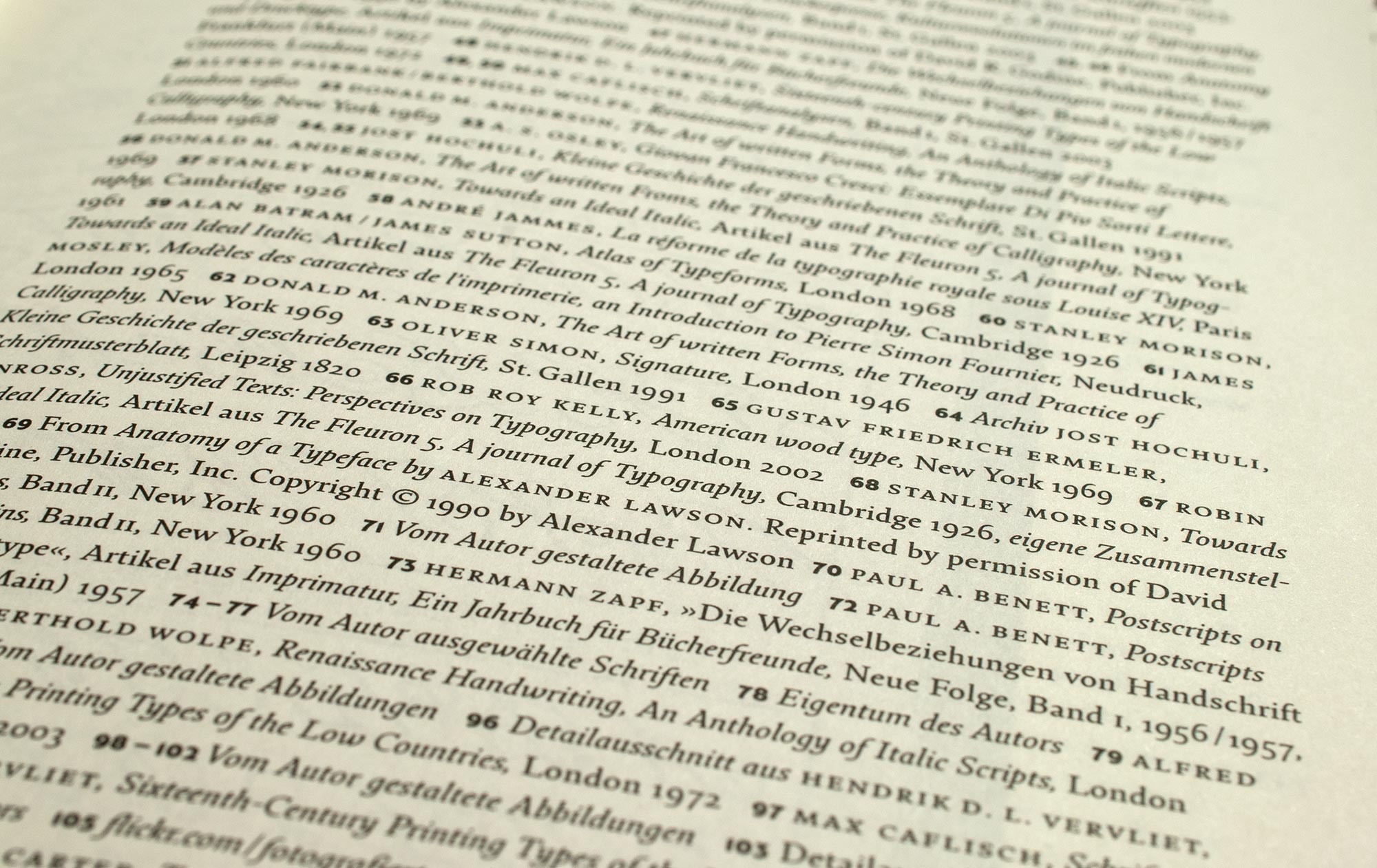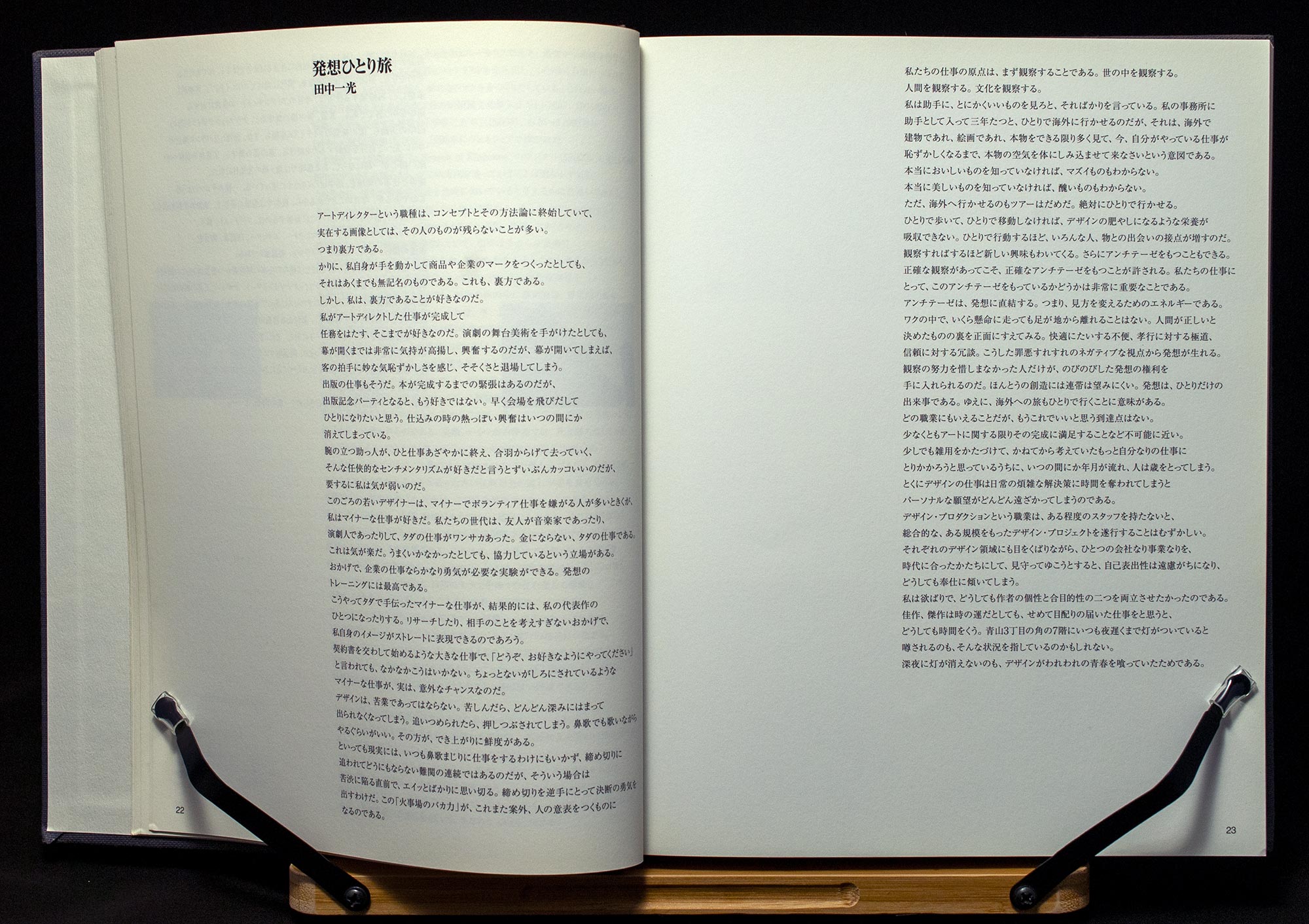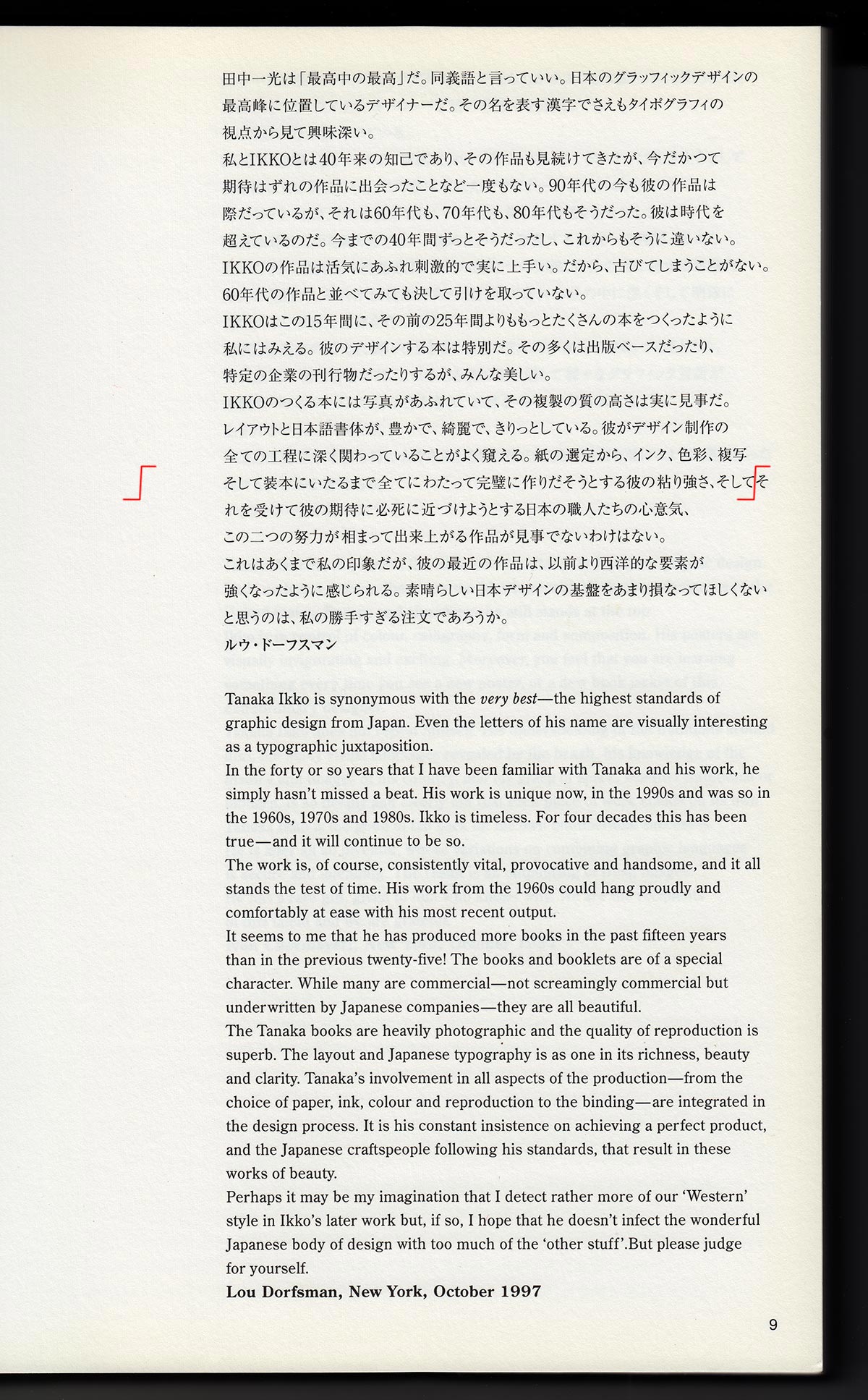
Flattersatz und Kursive im Japanischen
»Kursiv – Was Typographie auszeichnet« von Hendrik Weber, 2010
Was in der europäischen Typografie selbstverständlich ist, muss es deswegen noch lange nicht auch in der japanischen sein. Typische Beispiele.
Japanische Texte flattern nicht
In den meisten geschriebenen Sprachen der Welt werden Wörter voneinander getrennt. Die Zeilen werden bei Wortfugen umgebrochen. Die Zeilenlänge variiert ständig, weil die Wörter unterschiedlich lang sind. So entsteht der Eindruck, dass die Texte flattern. Aber Japanisch wird ohne Leerzeichen geschrieben und abgesehen von wenigen Ausnahmen kann ein Zeilenumbruch mitten im Wort nach jedem Schriftzeichen erfolgen. Deswegen gibt es in der Regel im Japanischen keinen Flattersatz, wie er in westlichen Texten verbreitet ist. Für japanische Texte wird in den allermeisten Fällen Blocksatz verwendet.
Wo jedoch kein Bocksatz erwünscht ist, z.B. bei diversen Überschriften, Teasern oder Bildunterschriften, werden Texte in Form von Flattersatz gesetzt, wobei sich die Zeilenumbrüche nicht nach dem verfügbaren Platz, sondern immer nach inhaltlichen Erwägungen richten.
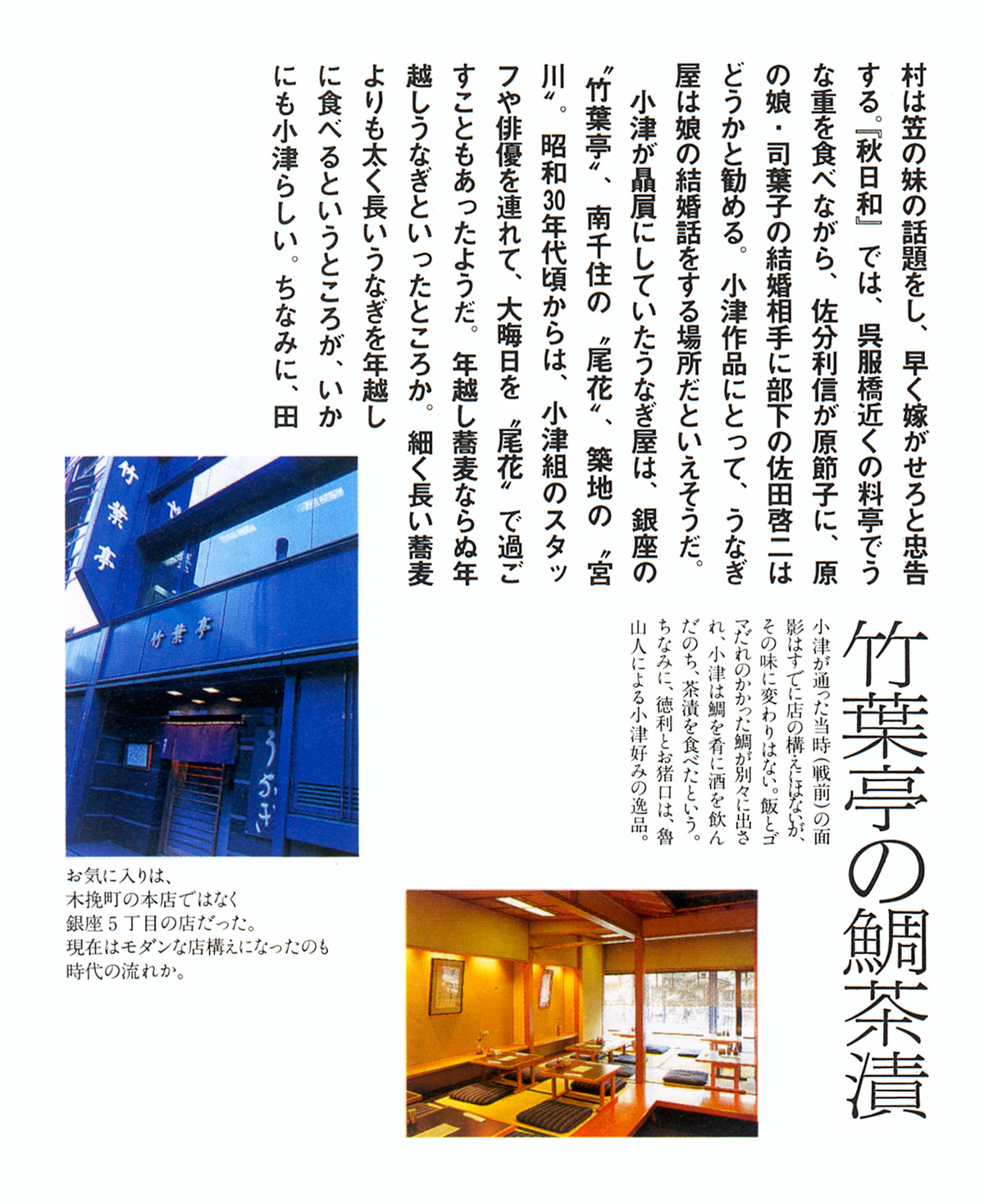
Zwei Bildunterschriften, zwei Satzarten.Die eine in Blocksatz, die andere (links) in Flattersatz japanischer Art. Sie sieht fast aus wie ein Gedicht.
Andere typografische Merkmale: Im oberen Haupttext kann man zwei verschiedene Arten von Anführungszeichen beobachten.
Flatternde Überschrift und Teaser. Ausschnitt aus einer Zeitschrift: Ob sich der Text gut liest, hängt stark vom Talent des Setzers ab.
Andere typografische Merkmale: Der lange Querstrich in der Mitte ist eine Art japanischer Gedankenstrich, der aus zwei nebeneinander gesetzten Geviertstrichen besteht. Er ist deshalb so lang, weil man einen einzelnen Geviertstrich leicht mit dem Schriftzeichen für »Eins« verwechseln kann, das einem Querstrich gleicht (mehr zu diesem Thema).
Namen von Autoren oder Fotografen gleich doppelt, zweisprachig in Japanisch und Englisch zu setzen, ist in Japan eine beliebte Praxis, auch wenn es überhaupt keinen Sinn hat. Es scheint bei vielen Japanern das Bedürfnis zu geben, irgendwo im Text auch lateinische Buchstaben zu verwenden, und dies erscheint ihnen als der einfachste Ort, da sie meinen, hier kaum etwas falsch machen zu können.
Eine fremde Schrift zu setzen, wird für eine einfache Sache gehalten, aber wie man in diesem Beispiel an den übergroßen Wortzwischenräumen gut erkennen kann, haben viele japanische Setzer noch eine Menge zu lernen, wenn es darum geht, Textstücke in lateinischer Schrift ansehnlich zu setzen.
»Falsche« Kursive
Kursive Auszeichnungen sind in den meisten Sprachen sehr beliebt und werden häufig verwendet. Zitate, besondere Betonungen oder Buchtitel sind die typischen Einsatzgebiete der Kursiven. Aber bedauerlicherweise kann dieses praktische typografische Instrument im japanischen Text nicht eingesetzt werden, denn es gibt keine kursive japanische Schrift. Kursive Schrift entsteht nur bei horizontaler Schreibrichtung. Zwar schreiben Japaner heute auch waagerecht, aber ihre gesamten Schriftzeichen entstanden noch in jener Zeit, als sie ausschließlich senkrecht schrieben. In heutigen Textverarbeitungsprogrammen kann man durch einen Knopfdruck jedes Schriftzeichen elektronisch »verschiefen« aber diese Funktion müsste aus Sicht eines Typografen eigentlich verboten werden.
In Japanischen Texten sieht man allerdings manchmal eine kursiv-ähnliche Auszeichnungsmethode. Sie ist in der Ära der Fotosetzmaschinen entstanden und wird heute noch angewendet. Dabei werden Schriftzeichen meist in vertikaler Richtung geneigt (früher optisch, heute elektronisch). Die so manipulierten Schriftzeichen wirken durch ihr Erscheinungsbild auf den Leser »ungewöhnlich«. Sie sollen seine Aufmerksamkeit auf sich ziehen und seine Neugier wecken. Sie werden aber eher als künstlich empfunden und werden keineswegs so wahrgenommen wie die Kursive in der europäischen Typografie.
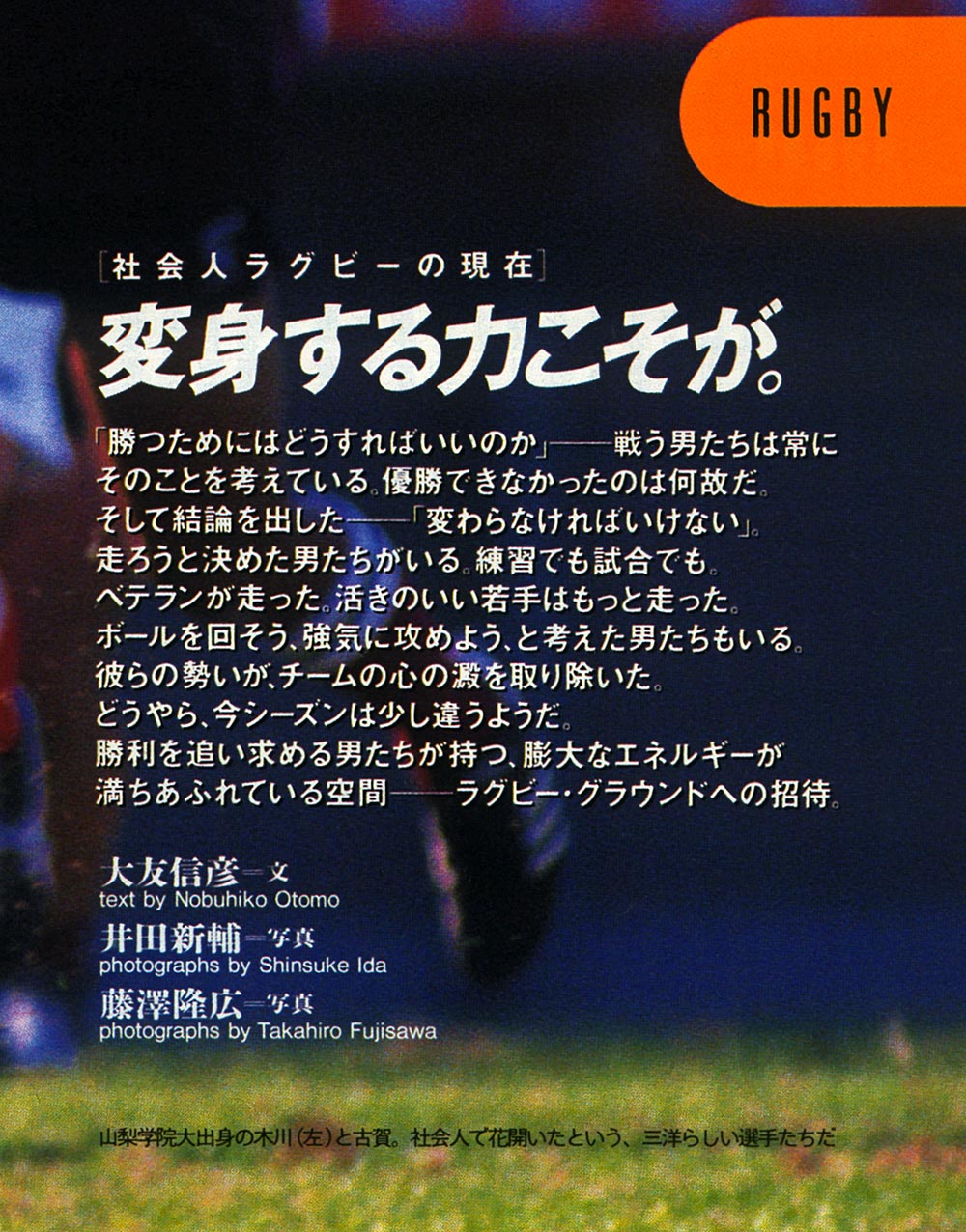
Blickfang 1.Ausschnitt aus einer Zeitschrift: Die Schriftzeichen der Überschrift sind geneigt und extrem eng gesetzt. In dem Artikel geht es um Sport, dazu passen die Schriftart und der dynamische Effekt sehr gut.
Andere typografische Merkmale: Flattersatz, Gedankenstriche und überflüssige englische Zeilen findet man hier auf engstem Raum vereint.
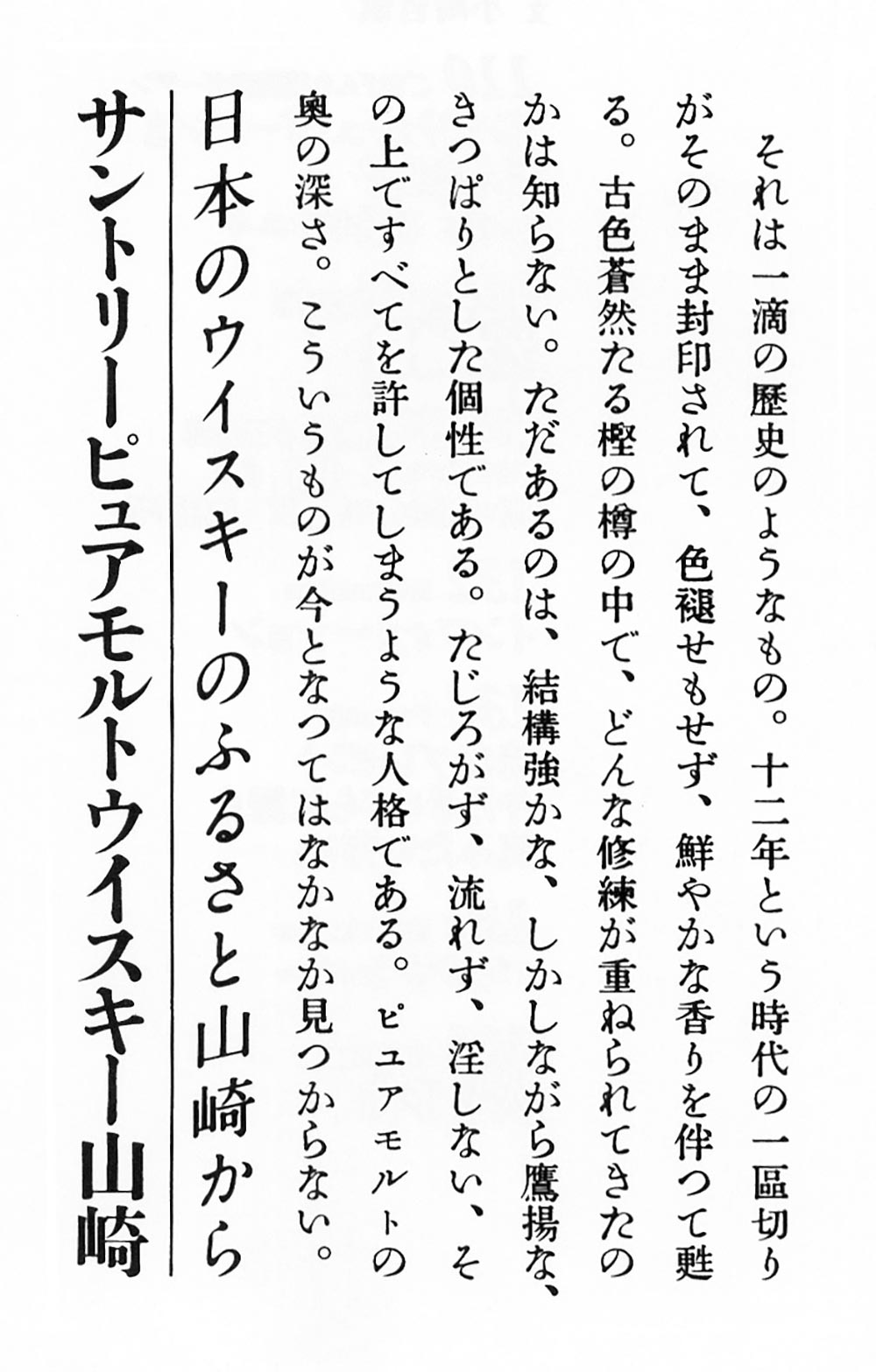
Blickfang 2.Werbetext für den japanischen Whisky Yamazaki: Die letzte Zeile (links) ist der Produktname, die vorletzte ist quasi der Slogan als Blickfang.
Andere typografische Merkmale: Die im Copytext verwendete Kana-Schrift Schuei Kana No. 5 (Größe 5) ist eine der ersten modernen japanischen Buchdruckschriften, die Anfang des 20. Jahrhunderts entworfen wurden. Auch sie wird von Morisawa vertrieben. Ihr traditioneller Look ist wohl der Grund dafür, dass sie ausgewählt wurde, um für einen zwölf Jahre alten Whisky zu werben.
- Flattern japanische Texte doch?
»Ikko Tanaka – Tradition and Design today«, 1998
In der Tat habe ich hier ein interessantes Beispiel für einen japanischen Pseudo-Flattersatz. Es handelt sich um einen Katalog über die Arbeiten von Ikko Tanaka (1930–2002), der bis heute einer der einflußreichsten japanischen Grafikdesigner ist und als der Urvater des Grafikdesigns in Japan gilt. Der vorliegende Katalog wurde von seinem eigenen Designstudio gestaltet, d.h., dieser Pseudo-Flattersatz ist kein Fehler sondern durchaus so gewollt.
»Ikko Tanaka – Tradition and Design today«, 1998
Beim Blocksatz kann so etwas nicht passieren. Also bitte nicht nachmachen und japanischen Fließtext immer schön im Blocksatz setzen.